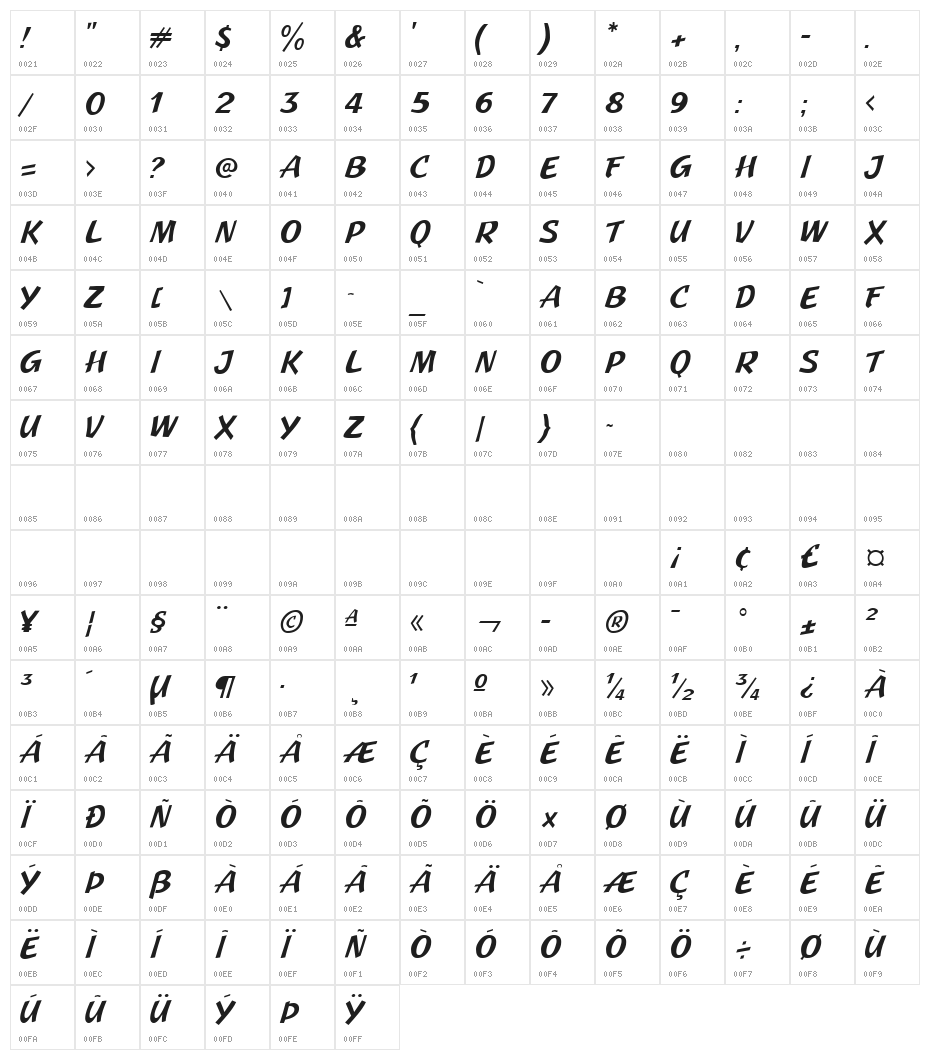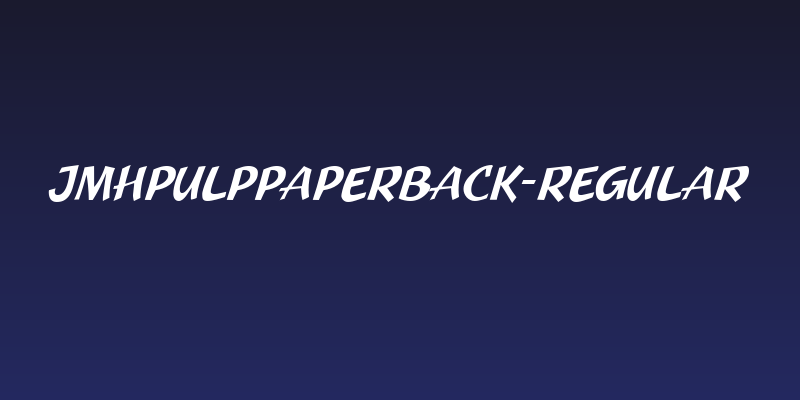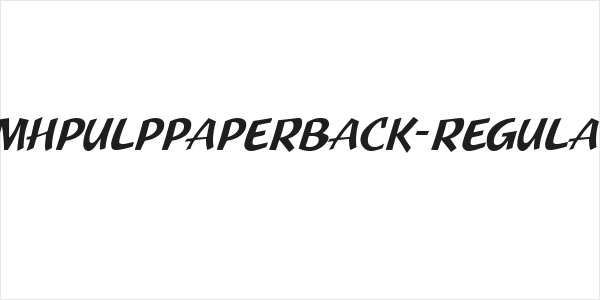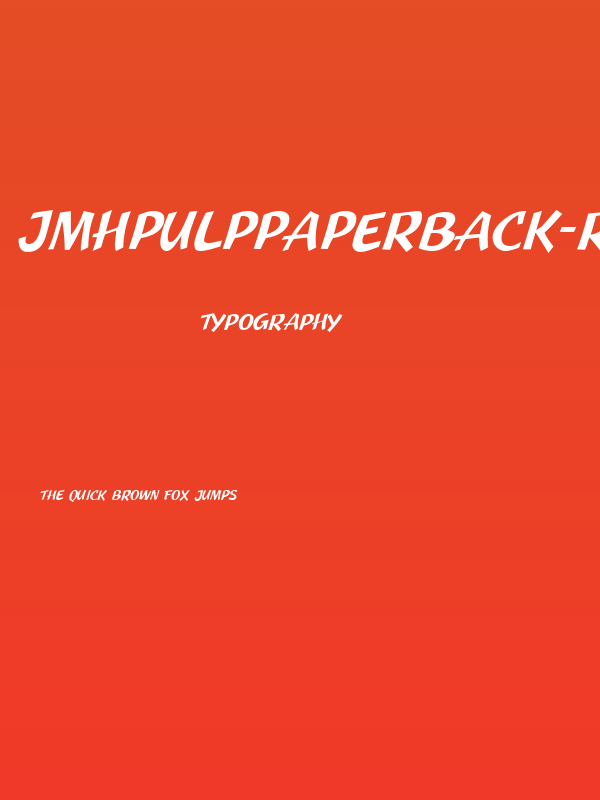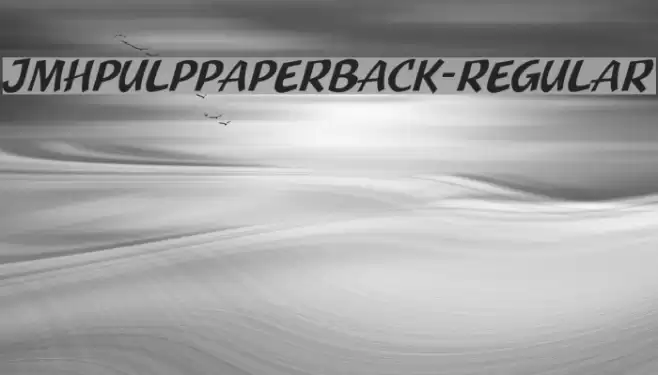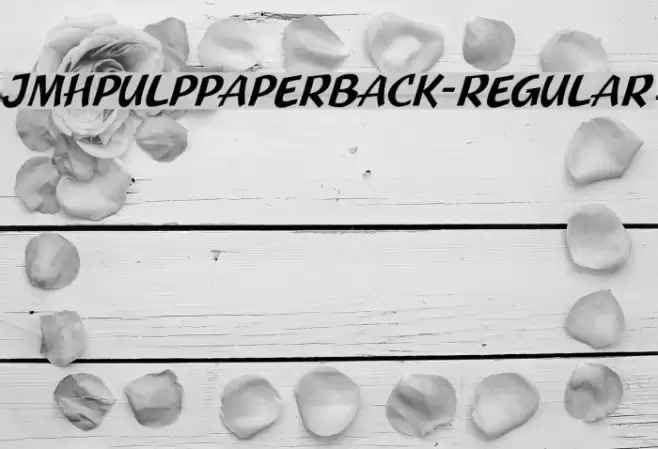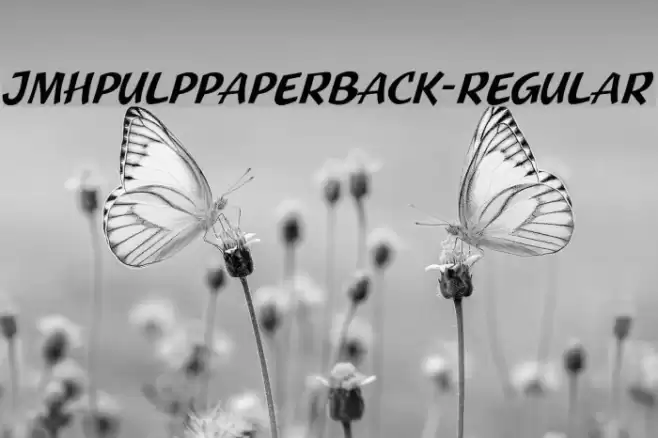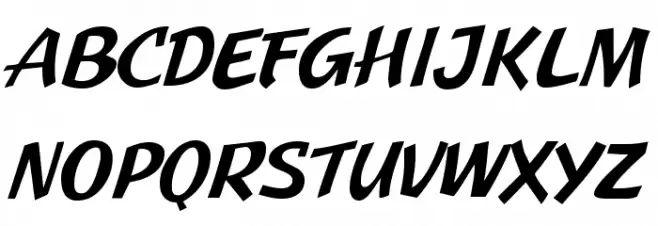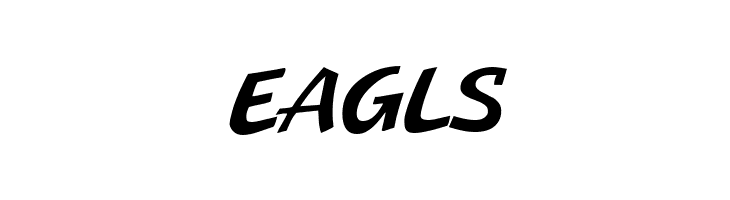
JMHPulpPaperback-Regular Font
| مائل | Yes |
| النمط العام | Vintage |
| مشاريع مقترحة | Ideal for book covers, posters, branding, and any project seeking a retro or dynamic aesthetic. |
| المؤلف | Fonts by Pablo Impallari |